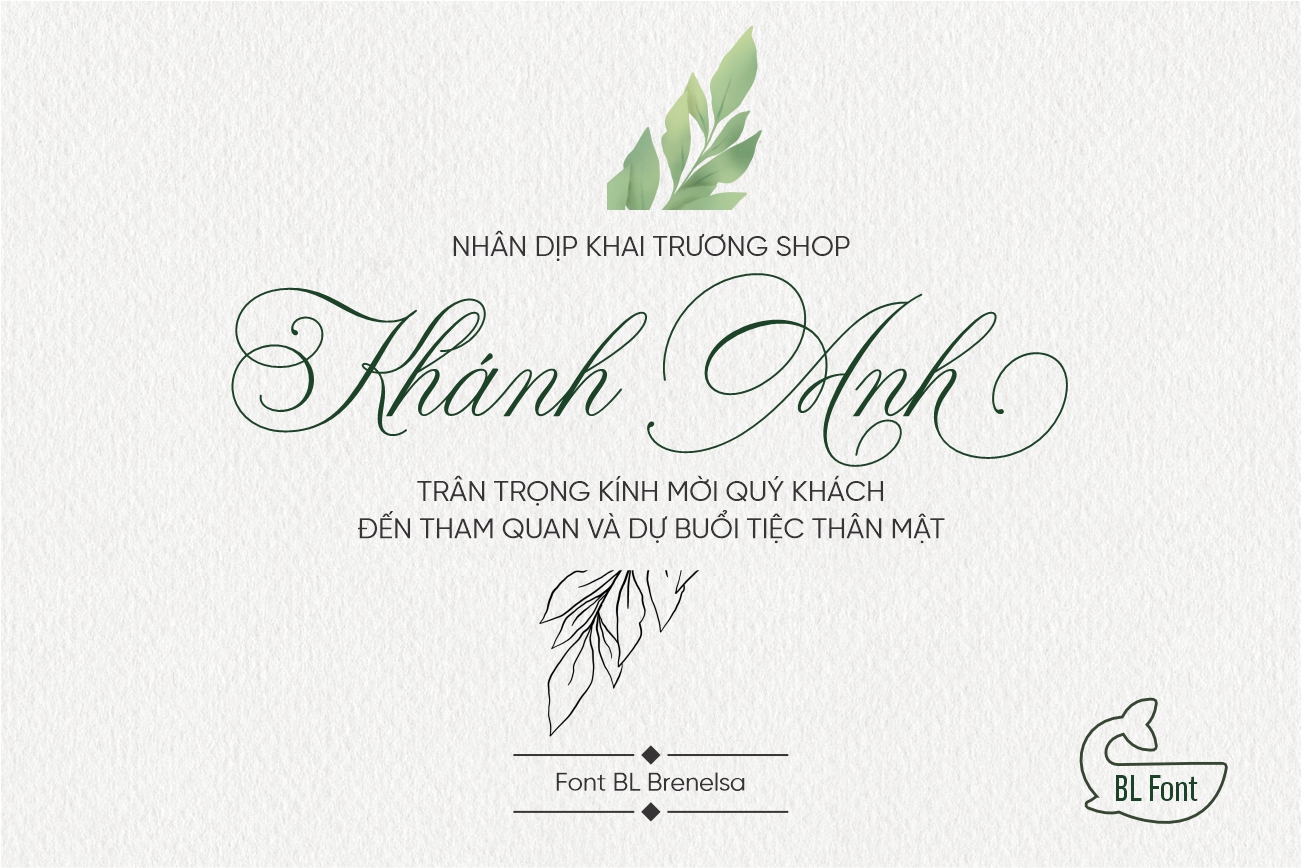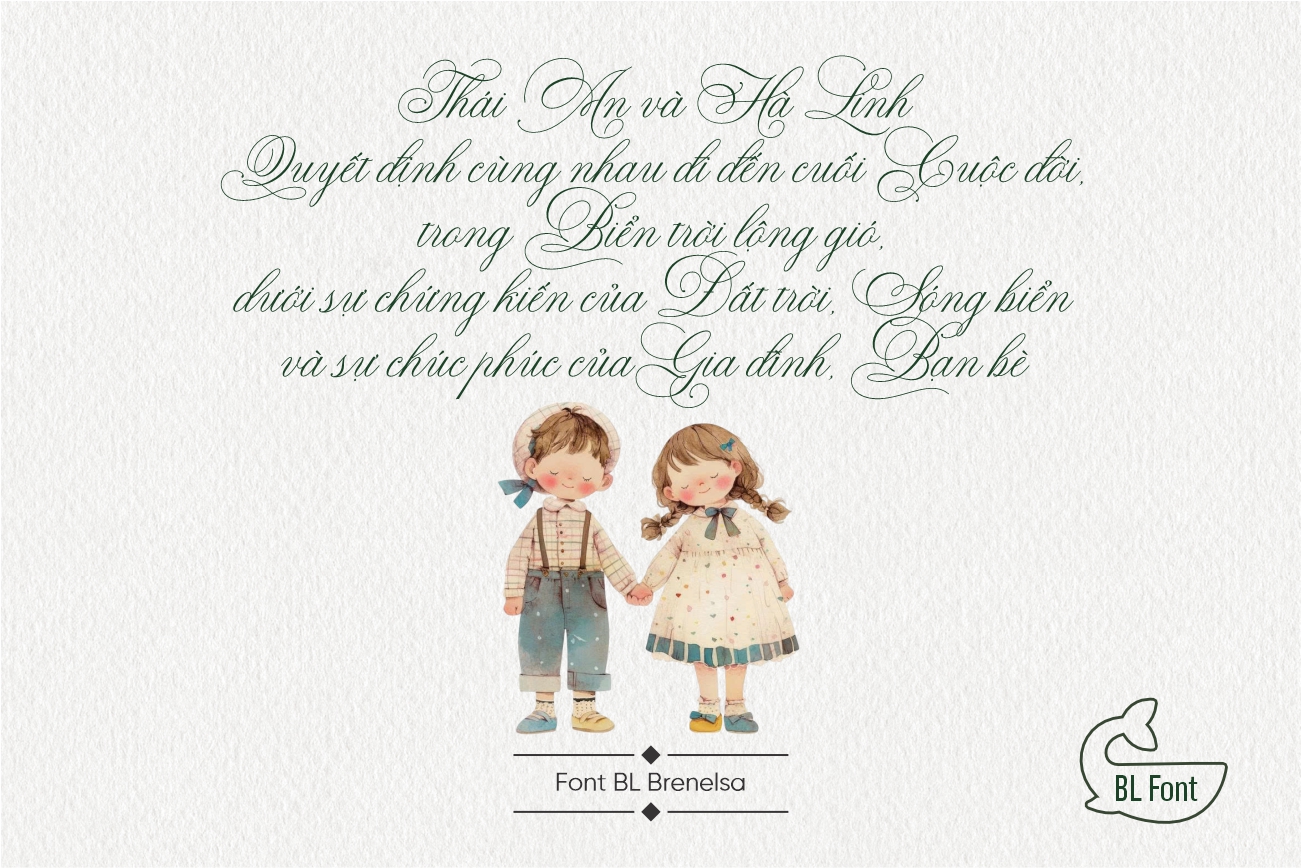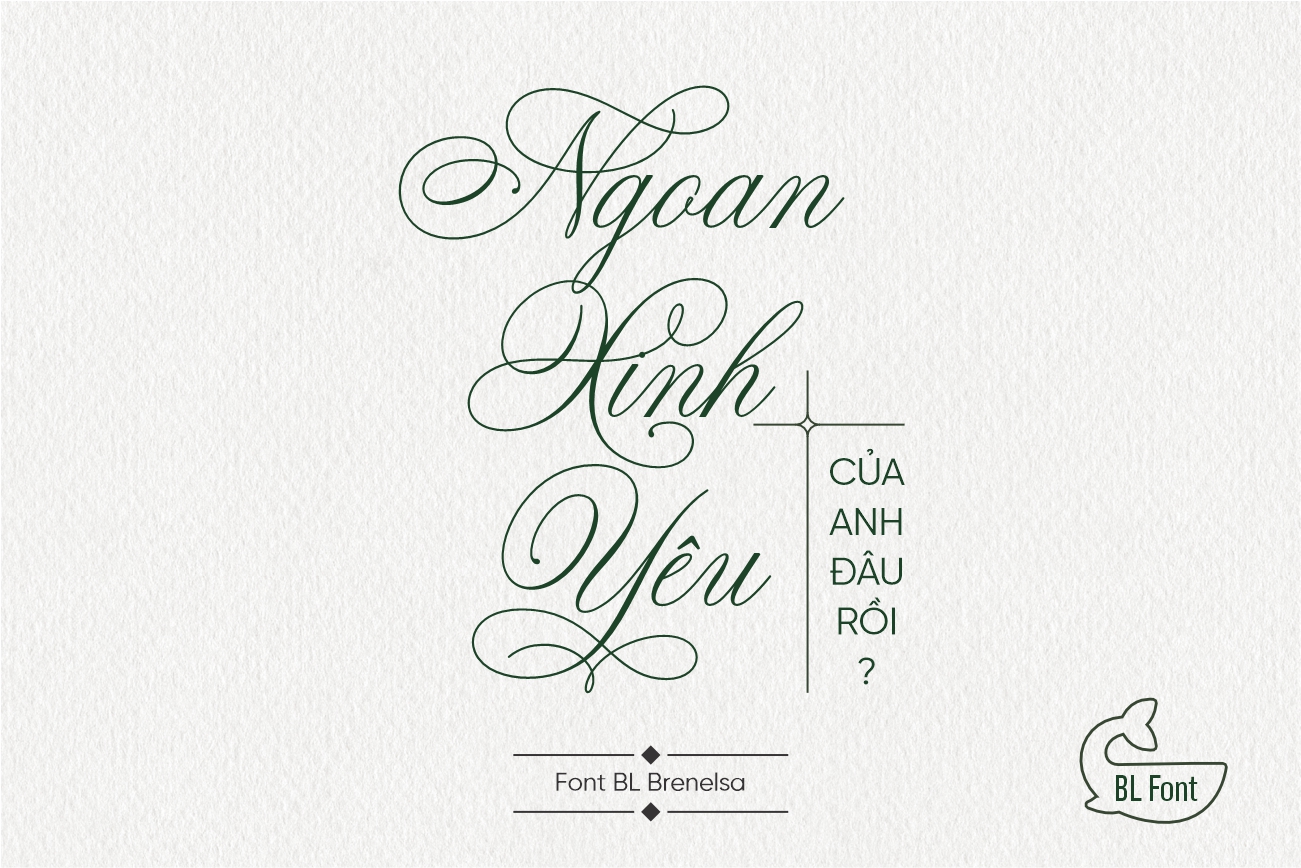
Font BL Brenelsa Việt Hóa – Sang Trọng, Lãng Mạn & Thanh Lịch
Trong thế giới typography, những font chữ viết tay luôn mang đến cảm xúc gần gũi và tinh tế. Nổi bật trong số đó chính là font BL Brenelsa Việt hóa, một bộ font mang đậm phong cách calligraphy với các đường nét uốn lượn mềm mại, đầy tính nghệ thuật. Đây là lựa chọn tuyệt vời cho các thiết kế cần sự sang trọng, lãng mạn và mang tính cá nhân hóa cao.
BL Brenelsa gây ấn tượng mạnh mẽ với những font chữ nét mảnh thanh thoát, kết hợp cùng các đường kéo dài duyên dáng ở đầu và cuối ký tự. Nhờ đó, từng con chữ hiện lên đầy sự uyển chuyển, nhẹ nhàng nhưng không kém phần quý phái. Font này đặc biệt thích hợp để sử dụng trong thiệp cưới, thư mời, logo thương hiệu cao cấp, bao bì mỹ phẩm hay các thiết kế liên quan đến thời trang và sự kiện.
Điểm cộng lớn nhất là font BL Brenelsa Việt hóa đã được hỗ trợ đầy đủ tiếng Việt với hệ thống dấu chuẩn đẹp, đảm bảo người dùng có thể dễ dàng áp dụng trong mọi dự án thiết kế mà không lo lỗi ký tự. Sự kết hợp giữa tính thẩm mỹ cao và khả năng ứng dụng linh hoạt giúp Brenelsa trở thành một trong những font calligraphy đáng sở hữu nhất hiện nay.
Nếu bạn đang tìm kiếm một font chữ viết tay vừa tinh tế vừa thể hiện được phong cách cá nhân, BL Brenelsa chắc chắn sẽ không làm bạn thất vọng. Với thiết kế chuẩn mực, thanh thoát và trọn bộ tiếng Việt, đây chính là một font chữ nét mảnh lý tưởng để tạo nên những sản phẩm thiết kế giàu cảm xúc và khác biệt.